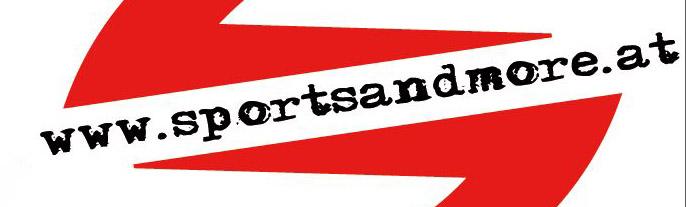
Suche "Grunge" Schrift aus dem Logo von Sports & More
ich hoffe ihr könnt mir helfen. Ich suche die Schrift aus einem Logo eines Bike-Stores. Die Webadresse (www.sportsandmore.at) im Logo ist mit diesem Font gestaltet.
Anbei das Logo.
Hier schreibt Bartek Nowak http://nowak.tv/machina-g/
The Machina font family consist of two typewriter fonts: MachinaR and MachinaG.
Machina G is a new, completely redesigned and improved version of my font Maszyna AEG, which was released for the first time in 2001.